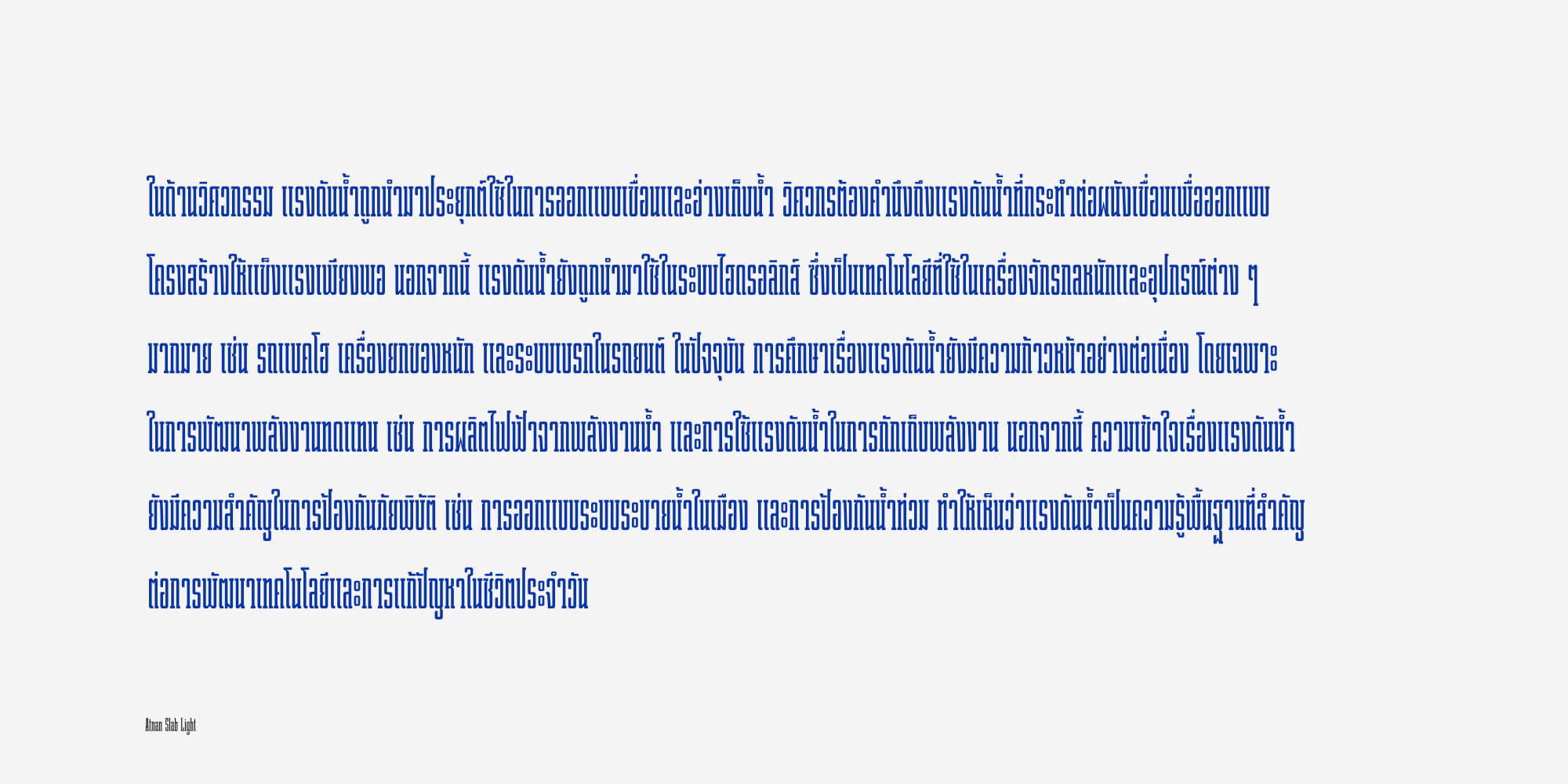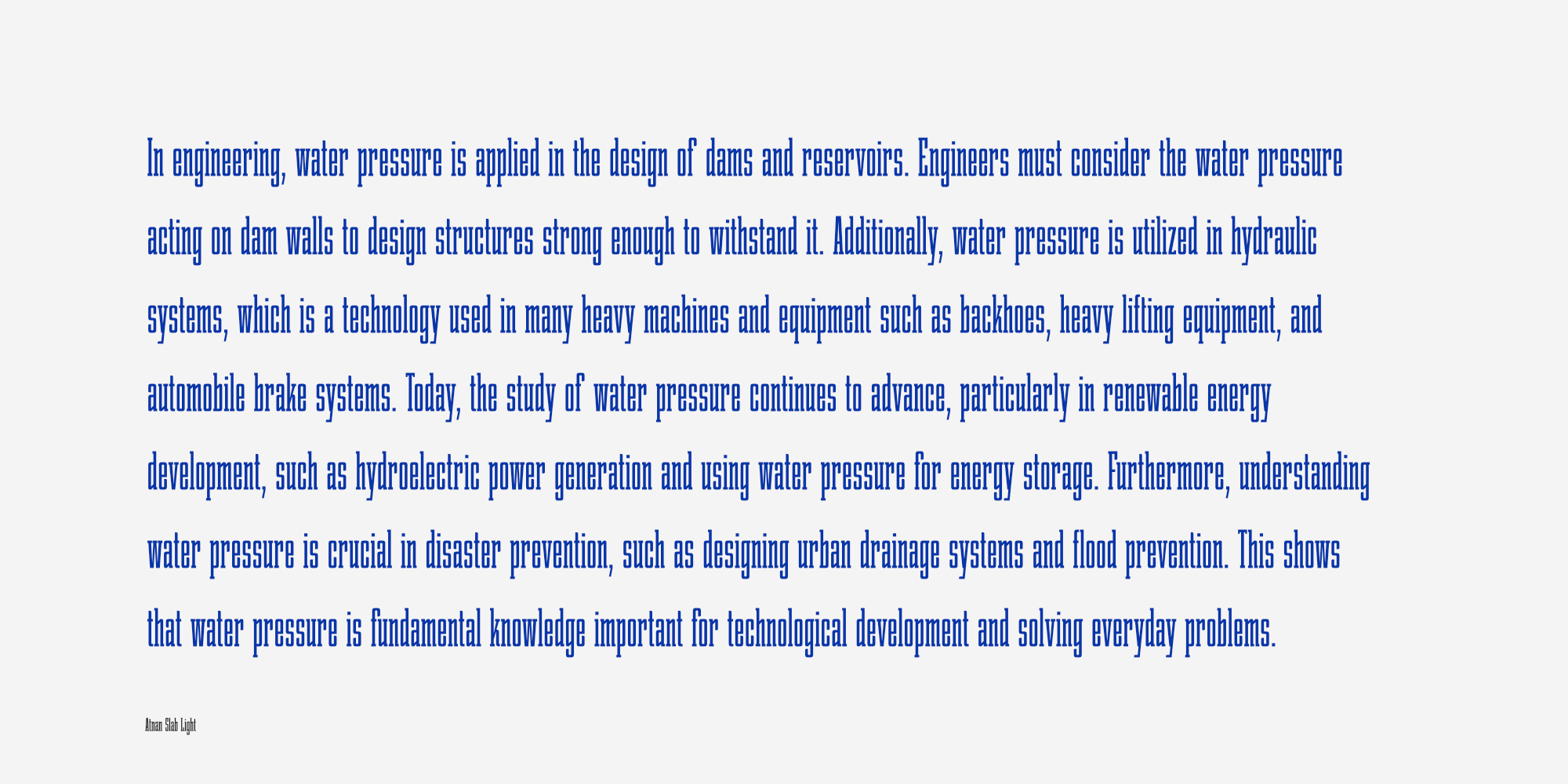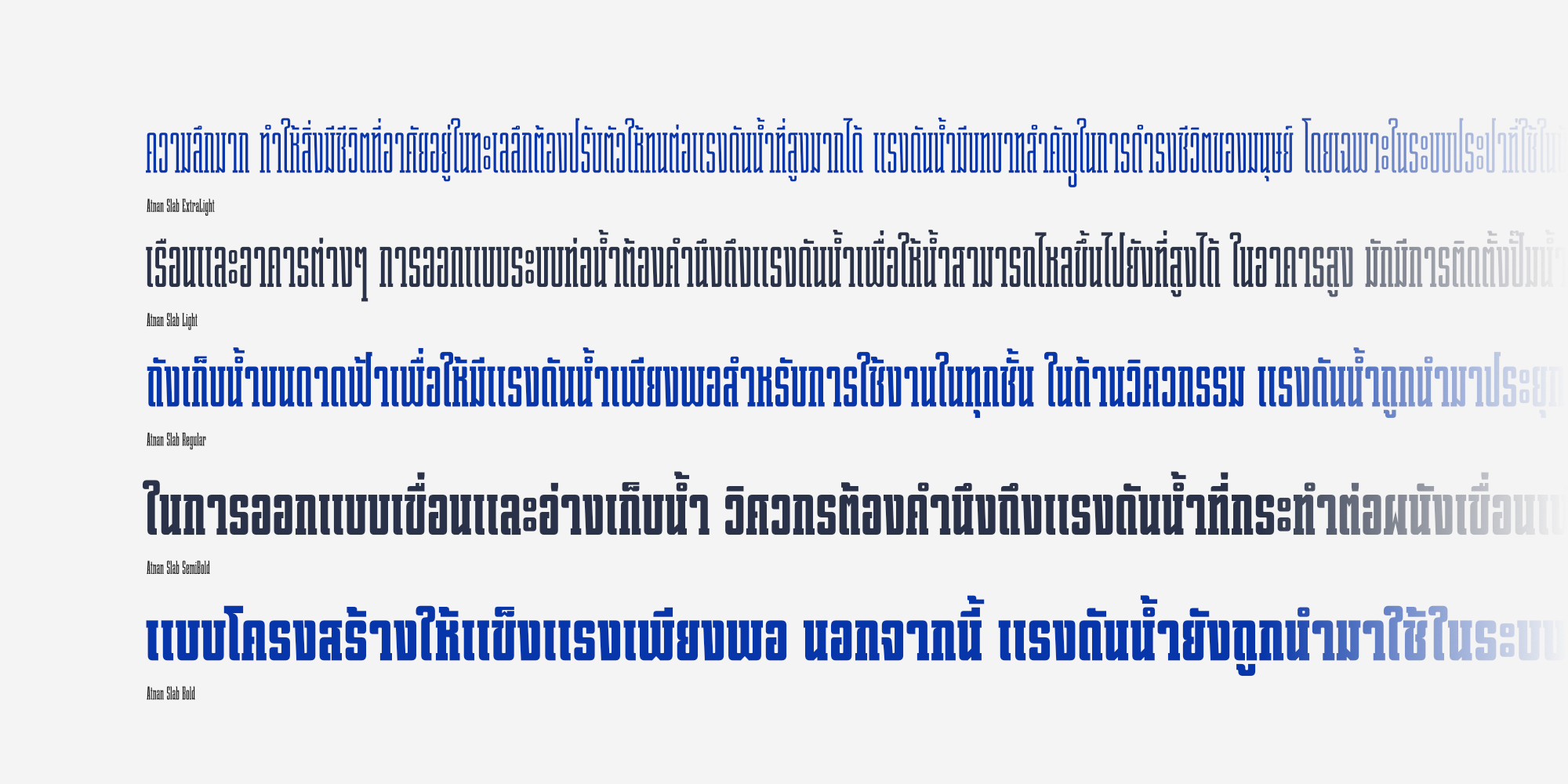
อัดแน่น สลับ | Atnan Slab
ชื่อฟอนต์ : อัดแน่น สลับ | Atnan Slab
อัดแน่น สลับ เป็นแบบอักษรสลับเซอริฟ ที่ออกแบบให้มีความแคบเป็นพิเศษ โครงสร้างตัวอักษรโดยรวมมีลักษณะเป็นสี่เหลี่ยมหลังแบน เหมาะสำหรับสื่อประชาสัมพันธ์ที่มีพื้นที่จำกัด หรือต้องการสร้างความน่าสนเมื่อใช้เป็นข้อความผาดหัว แบบอักษรนี้ประกอบด้วย 18 รูปแบบ ครอบคลุมน้ำหนักเส้นตั้งแต่บางที่สุดจนถึงหนาที่สุด โดยรองรับทั้งชุดอักษรลาติน 1 และอักษรไทย